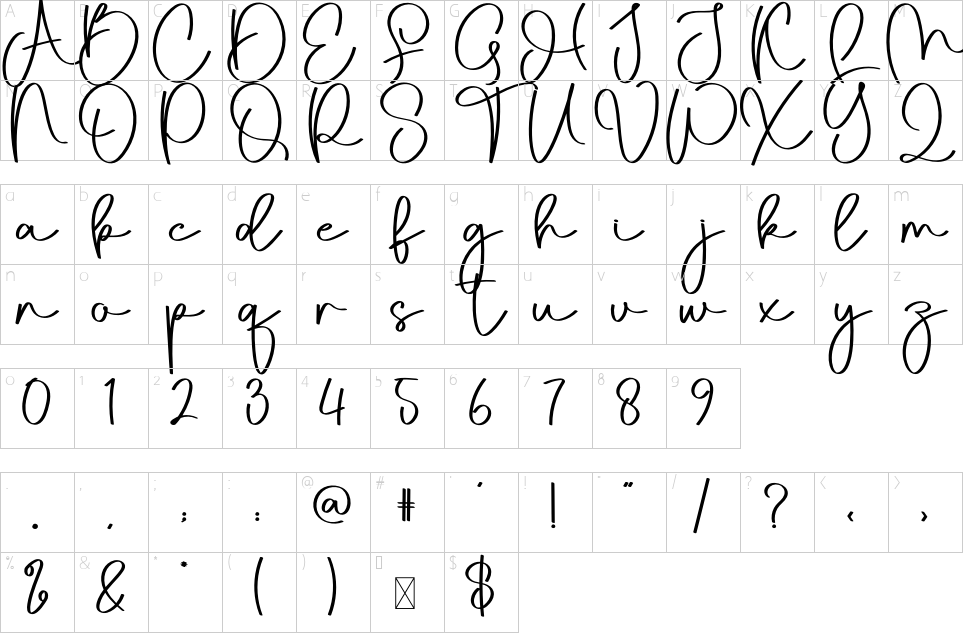
Aqui está uma descrição em português, envolvente e natural, para a página de download da fonte ‘Mountain Font | 1001 Free Fonts’: Sinta-se bem-vindo ao reino das fontes gratuitas! Nesta categoria, encontrará uma seleção de fonts únicas e versáteis, como a fonte Mountain, que adorarão designers e estilistas de sites. Inspirada na natureza majestosa das montanhas, essa fonte possui linhas levemente inclinadas e detalhes levemente ondulados, criando um efeito elegante e sofisticado. Ela foi projetada por um designer desconhecido, e já foi baixada mais de 425 vezes, demonstrando o seu valor e popularidade. Ideal para criar designs que combinem elegância com uma sensação de calma e tranquilidade. Baixe Mountain e enriqueça seu design com uma fonte que transmite a serenidade e força das montanhas.